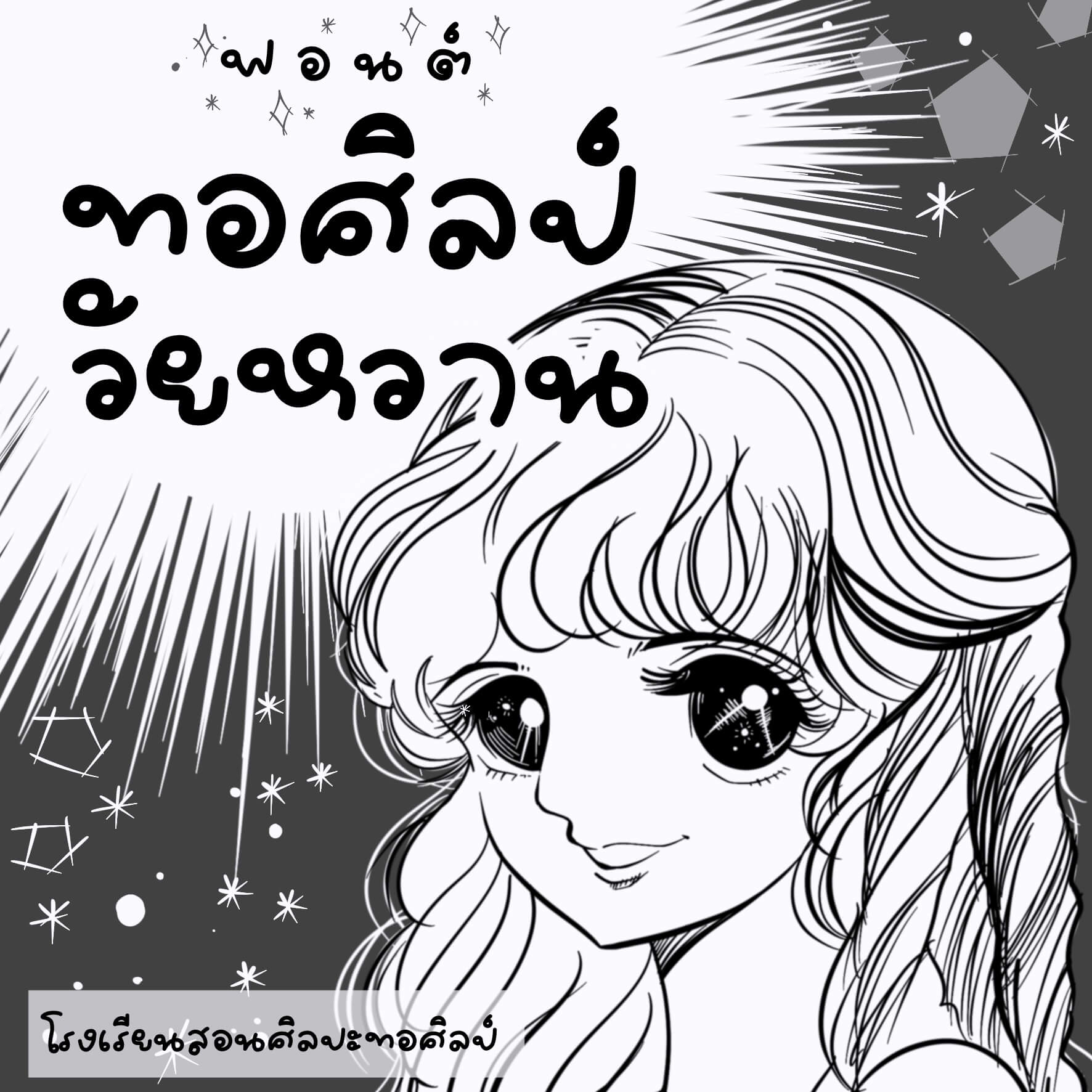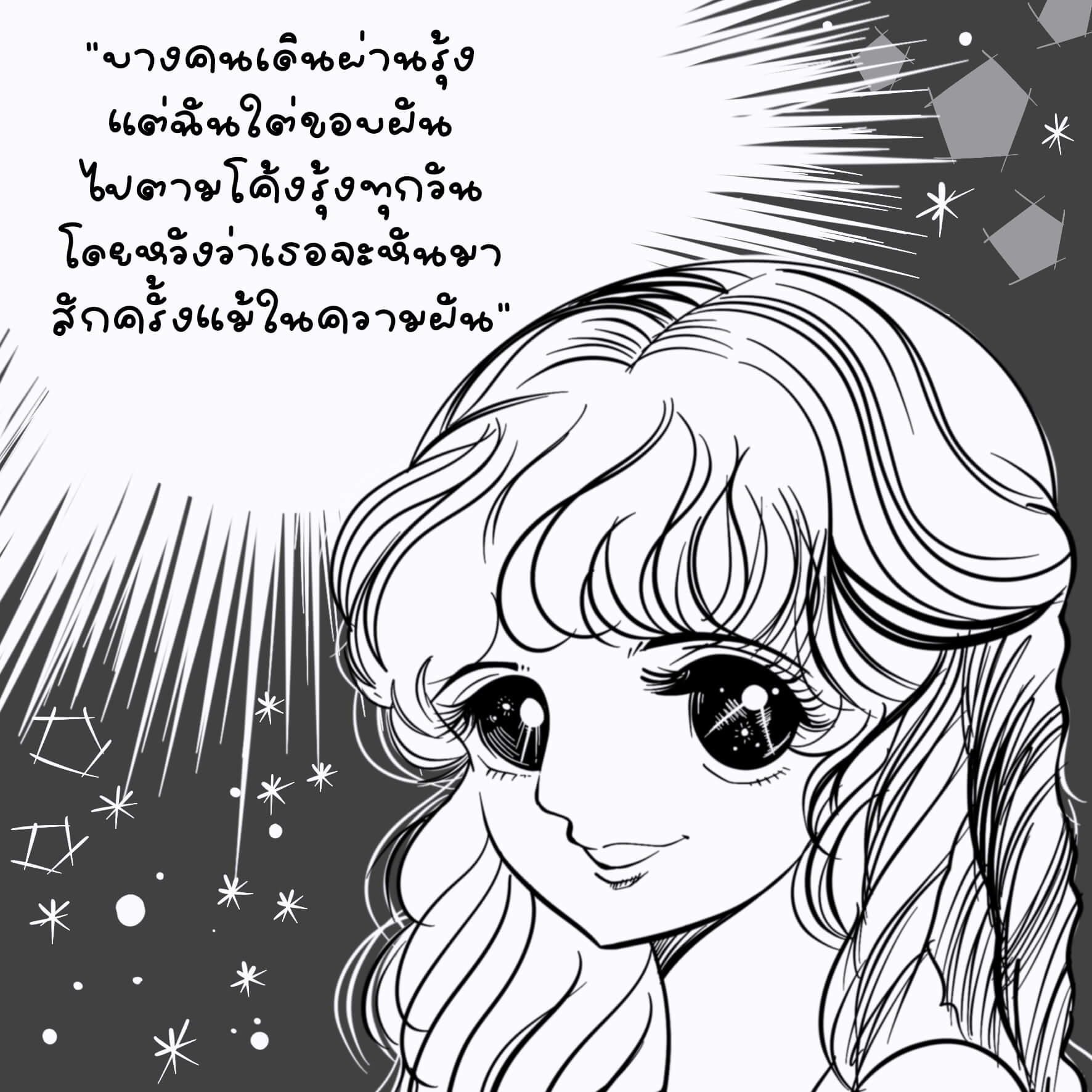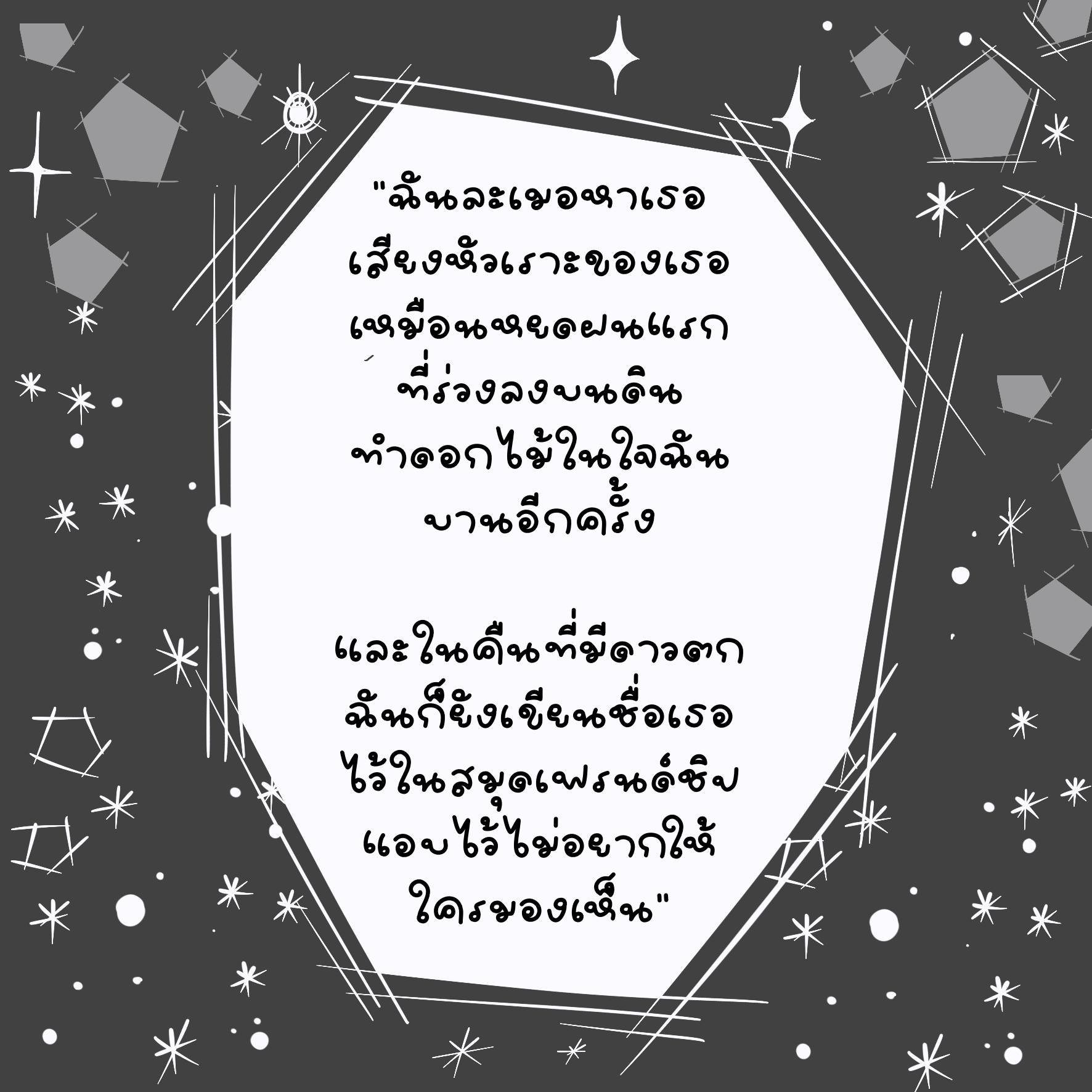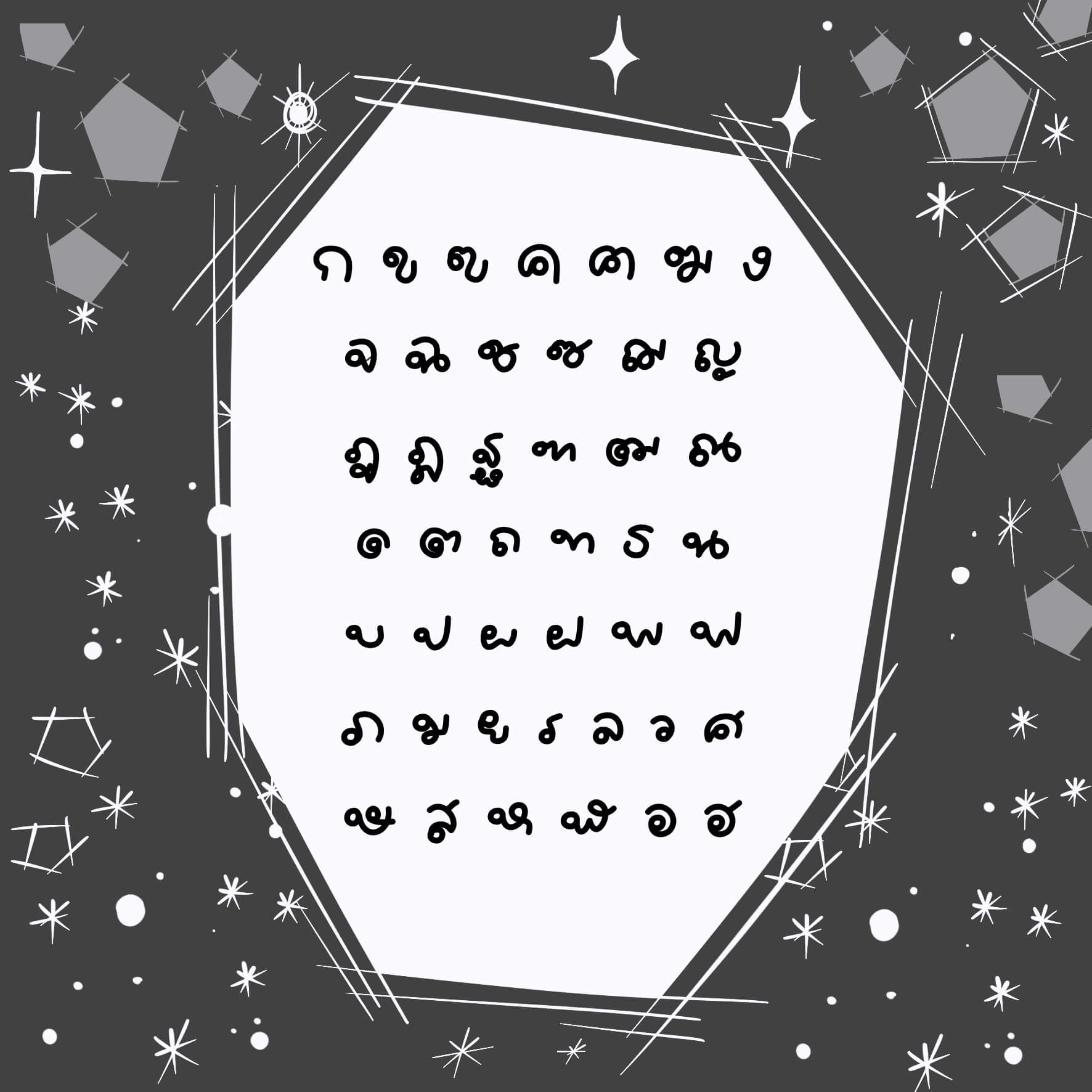
สมัยเรียนศิลปะ ยุคนั้นสมัยโน้น ลายมือแบบนี้นิยมมาก คุ้นตาจากนิตยสารวัยรุ่นประเภทวัยหวาน ใยไหม เป็นหนังสือกลอนเปล่า เฝ้าฝัน ละเมอหา ผมเองพยายามคัดฝึกลายมือแบบนี้อยู่เหมือนกัน กะว่าเอาไว้เขียนเฟรนด์ชิปสวยๆ
ทำไปทำมากลายเป็นอาชีพได้แบบบังเอิญ เพราะตามร้านกิ๊ฟต์ช็อปเขารับกลอนเปล่าที่วาดลงกระดาษไข
แล้วประกอบกลอนด้วยภาพการ์ตูนตาหวาน ทำเสร็จเอาใส่กรอบไม้กลมสีดำ ส่งขายตามออร์เดอร์ของร้าน รายได้ดีตามสมควรเลย
ทอศิลป์ วัยหวาน (Torsilp WaiWan)